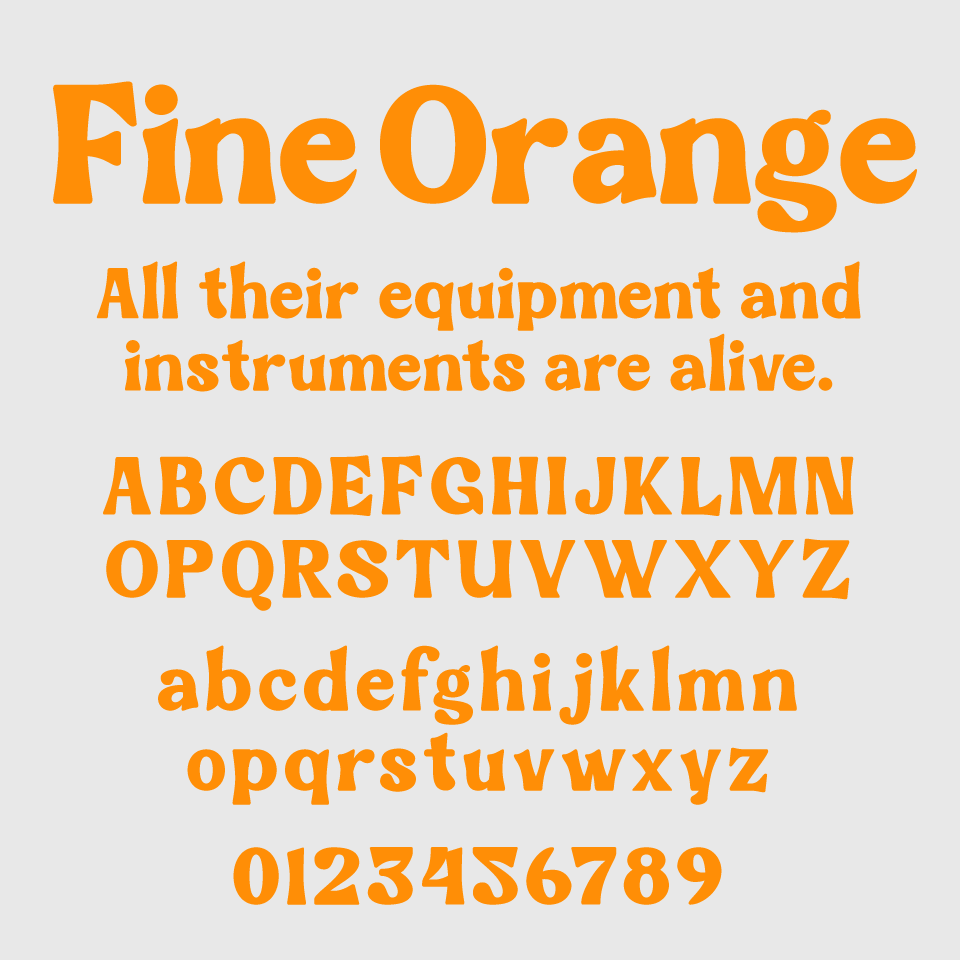
Fine Orangeフォントは、ぽってりとしたカーブと不規則な揺らぎが特徴的な、手作り感のあるユーモラスなセリフ体フォントです。
各文字に微妙な個体差があり、人の手で丁寧に描かれたような温度を感じさせます。ややレトロな雰囲気もあり、懐かしさと親しみのバランス感あるデザインです。
1文字に複数のデザインのグリフが用意されているので、組み合わせ方で表情が変わるユニークなフォントです。